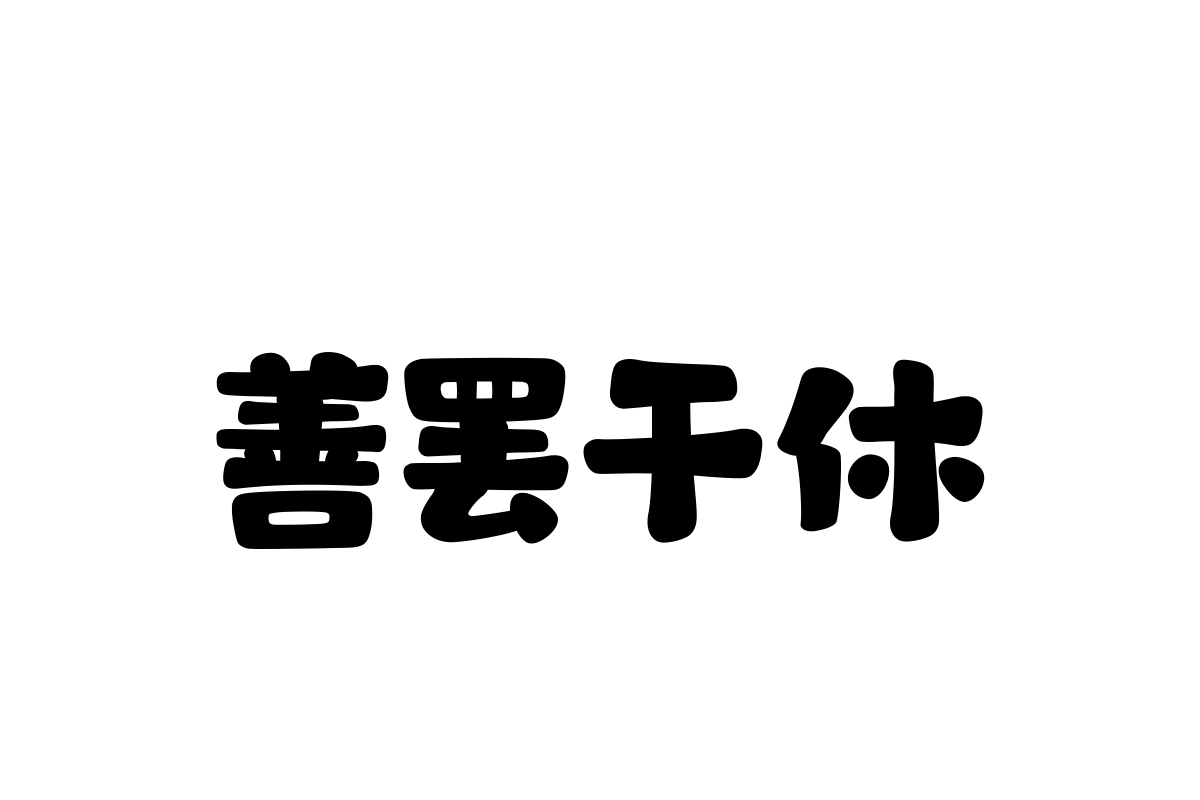
汉仪永字小熊猫字体是一款现代感十足、简洁大方的中文字体,具有很高的辨识度和美观度。它采用了独特的笔画结构和风格,使得文字呈现出一种活泼可爱的感觉,非常适合用于儿童书籍、杂志、广告、网页等场合。
该字体的特点是笔画流畅、结构紧凑,既有传统汉字的韵味,又不失现代感。它的字形圆润饱满,线条清晰有力,给人一种亲切、温馨的感觉。同时,该字体还具有一定的可读性,适合各种字体大小和排版方式。
总的来说,汉仪永字小熊猫字体是一款非常实用的中文字体,无论是在商业还是教育领域都有着广泛的应用前景。